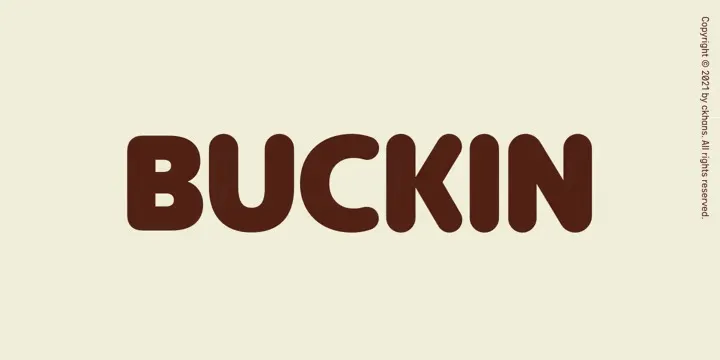
Buckin Font
A Buckin Font é uma família suave e agradável de tipo, que transmite uma aparência amigável e levemente descontraída, ideal para ambientes descomplicados e versáteis. Desenvolvida pelo designer Ckhans Fonts na plataforma 99designs, esta fonte vem em uma ampla gama de pesos (10), incluindo opções de uprights e obliques (20) que permitem um uso imaginativo e criativo para adaptá-la a diferentes ambientes. Ela oferece mais de 691+ glyphes, permitindo-lhe explorar seus potenciais inexplorados em uma variedade de cenários, desde identidades digitais até design gráfico, sem preocupação quanto à sobrecarga ou perda de estética por causa da diversidade de aparências. Uma fonte que se destaca não apenas pela sua versatilidade e riqueza em detalhes, mas também pelo seu potencial único para dar vida a qualquer projeto.